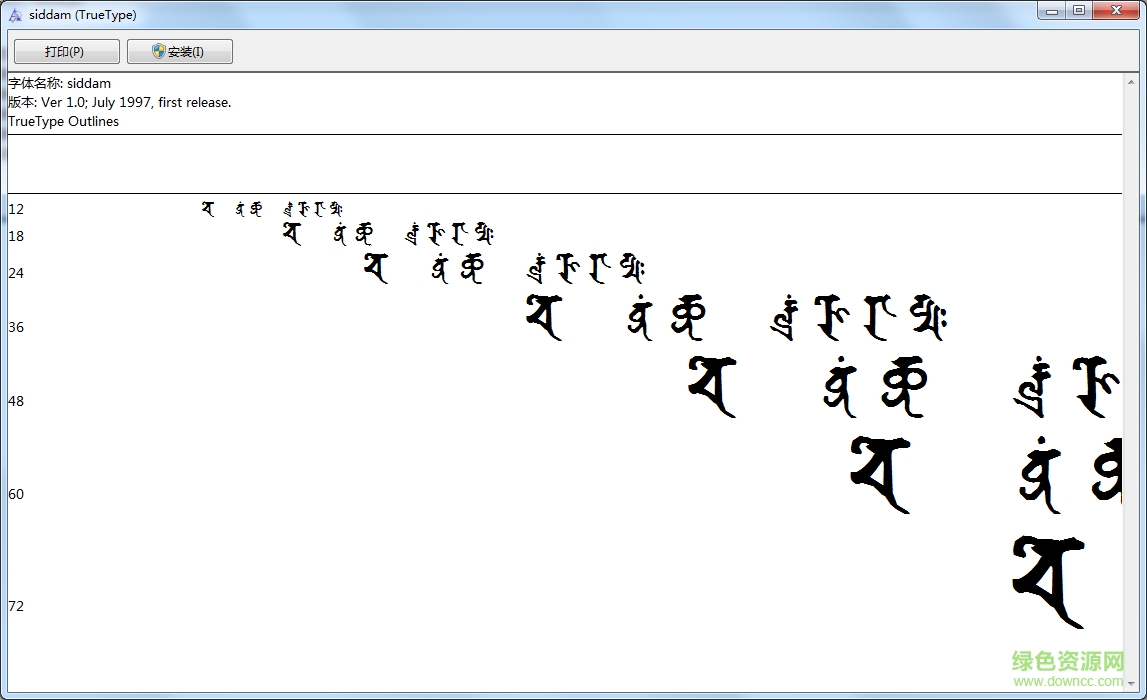
悉昙梵文字体是一款非常好用的梵文字体,梵文在佛教中使用非常的广泛,字体非常的刚劲有力,也非常的漂亮,欢迎有需要的朋友到绿色资源网下载使用!
悉昙梵字,也是梵文重要的组成部分,佛教中用来观想,大多用的都是悉昙梵字,在日本东密的总本山高野山,就流传着世界上最为标准的悉昙梵文,从唐代唐密传入日本,至今依然留传着,属于最古老的悉昙梵字!